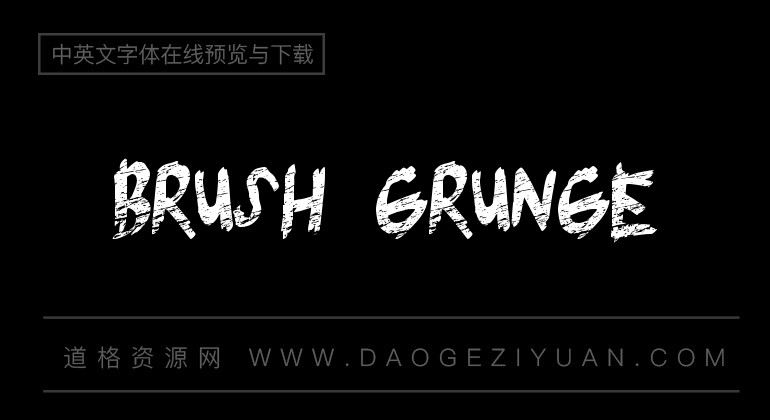
Brush Grunge
Brush Grunge 字体是一种手写风格的字体,具有独特的粗糙、不规则的笔画,仿佛是用刷子或油漆喷雾涂鸦而成。它的外观有点像涂鸦艺术,适用于需要具有另类感觉的设计和项目。Brush Grunge 字体包含大写字母、小写字母、数字和标点符号,可以在海报、书籍封面、标志、传单和网站设计等项目中使用。它的不规则特性和独特的外观可为设计添加个性和视觉吸引力。
Brush Grunge是一款非常不错的手写艺术字体,具有很好的视觉感,适合于文化类的宣传设计、商业类品牌的广告和产品包装设计以及个性化文字排版等较多场景。